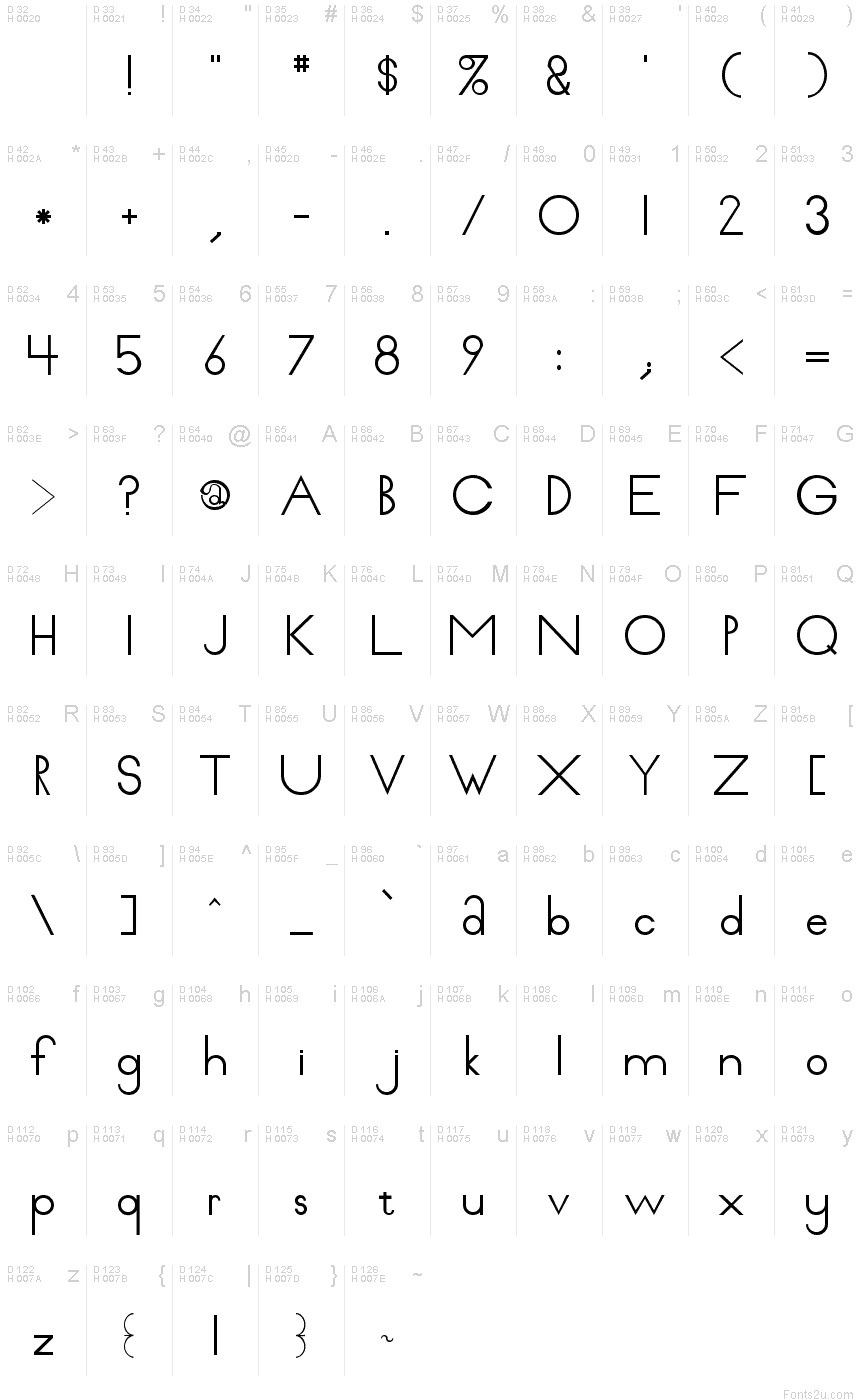
Pabloco
Pabloco to bezpłatny font typu display o zaokrąglonych, geometrycznych kształtach oraz bardzo otwartej, oszczędnej strukturze. Znaki są nakreślone płynnymi krzywiznami i prostymi pionowymi liniami, co nadaje literom spokojny rytm i charakterystyczną, niemal modułową konstrukcję.
Pabloco świetnie sprawdza się w logotypach, napisach, nagłówkach plakatów, projektach opakowań, systemach informacji wizualnej i grafikach do mediów społecznościowych, gdzie kształt liter ma tworzyć główny przekaz. Obszerne krzywe i czyste kontury nadają tym projektom wyrazisty charakter bez zbędnych zdobień, dzięki czemu font ten jest szczególnie polecany do krótkich, przyciągających wzrok tekstów.